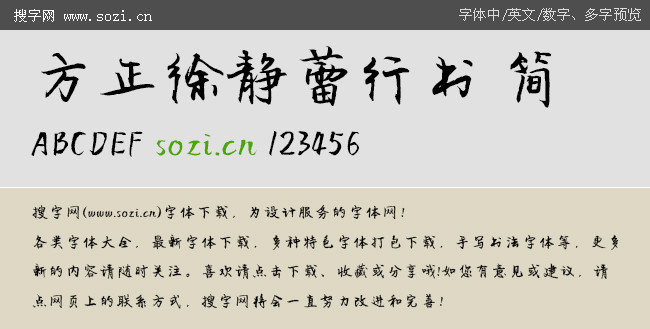
方正徐靜蕾行書簡(jiǎn)
搜字網(wǎng)提供一款方正徐靜蕾行書簡(jiǎn)中文字體下載,方正徐靜蕾行書由知名影視演員、導(dǎo)演徐靜蕾創(chuàng)作。這款字是靜蕾體推出十年后創(chuàng)作的。徐靜蕾自幼習(xí)書,有十年顏體功底,這款行書體繼承了靜蕾體骨骼,結(jié)構(gòu)清秀、遒勁有力,個(gè)性優(yōu)雅從容。適用于現(xiàn)代詩(shī)歌、短文的排版,以及文化、商業(yè)類品牌的廣告語設(shè)計(jì)。